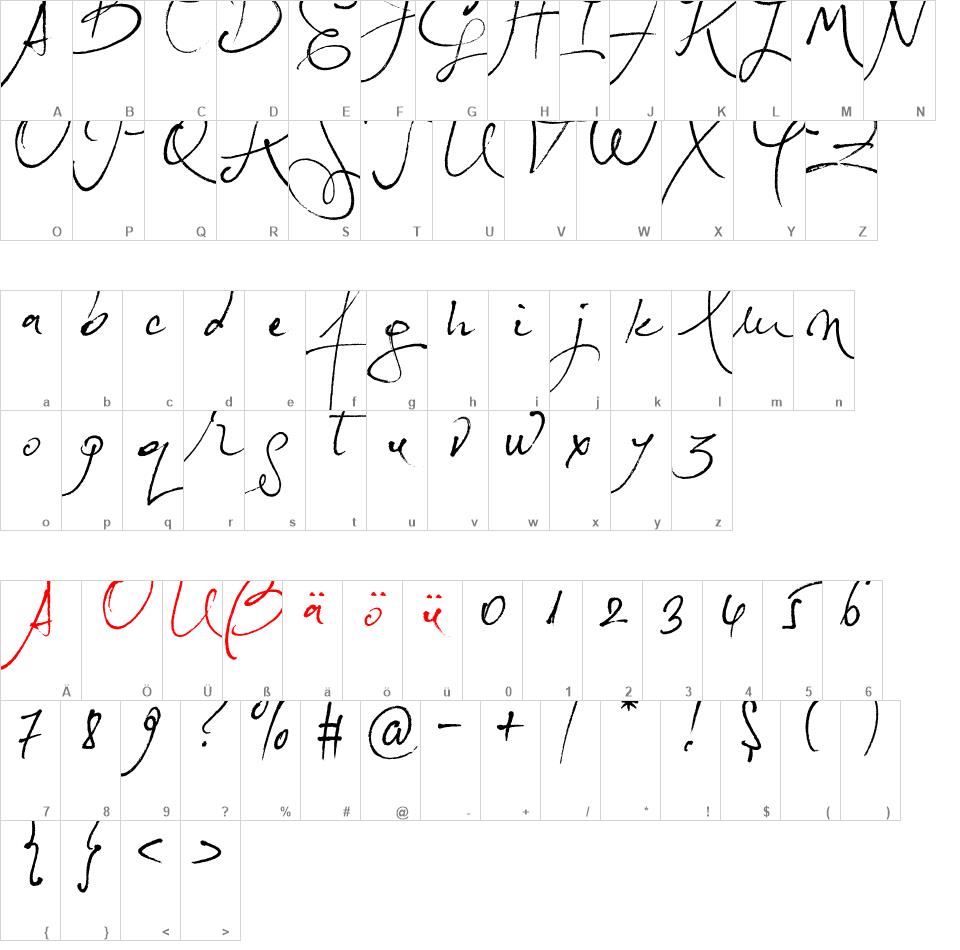
Loveletter No. 9
Liebesbrief Nr. 9 wurde natürlich aus Liebe zum Brief gemacht.
Um Wörter zu unterstreichen verwenden Sie den Underscore nach dem Wort oder nach drei / vier Buchstaben (Breite der Unterstreichung), zum Beispiel "The_", "Lovelet_ter", "Question_", nur für Anfänger.
Die Breite der Großbuchstaben ist so eingestellt, dass sie als Großbuchstaben verwendet werden, für Vollschlüsse kann etwas zusätzlicher Platz benötigt werden, ansonsten sehen Wörter wie lange Monogramme aus.
Einige der Briefpaarungen basieren auf schweren Kernings, daher ist es besser, die Schriftart mit Software zu verwenden, die diese Funktion enthält.